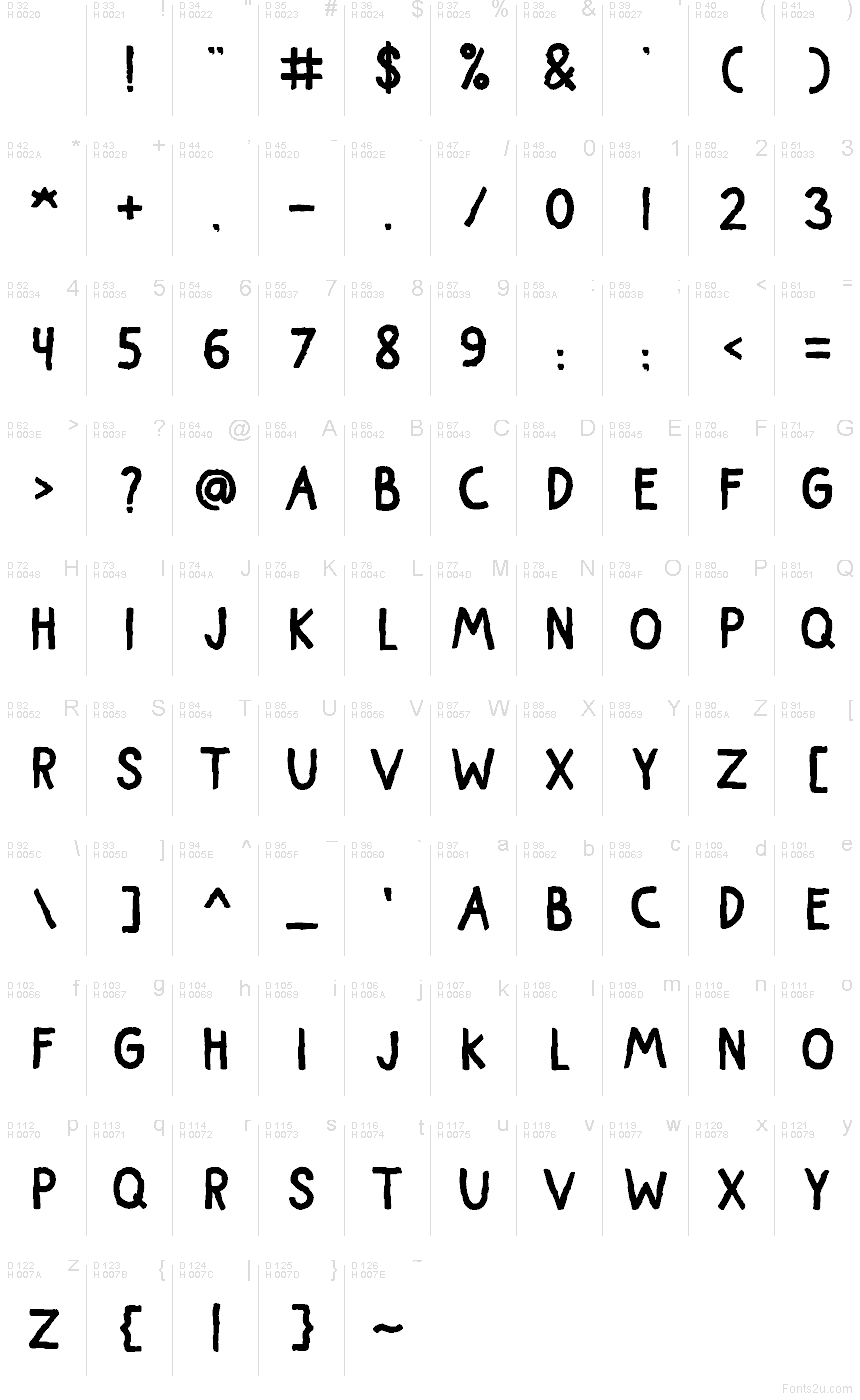
Tadiven
Tadiven od Tokokoo je bezplatné kreslené display písmo s ručne maľovaným dojmom. Písmená vyzerajú ako vyrezané z hrubých čiernych ťahov štetcom, majú nerovné okraje, robustné tvary a hravú nestabilitu, ktorá udržuje celú abecedu uvoľnenú a živú.
Vďaka tomu je tento bezplatný font prirodzenou voľbou pre titulky plagátov, obálky detských kníh, komiksové nadpisy, obaly a letáky na podujatia, kde hľadáte niečo výrazné a trochu neposlušné. Dobre funguje aj pre krátke titulky alebo monogramy, pretože široké, nepravidelné tvary pôsobia graficky a živo, aj keď použijete len niekoľko znakov.